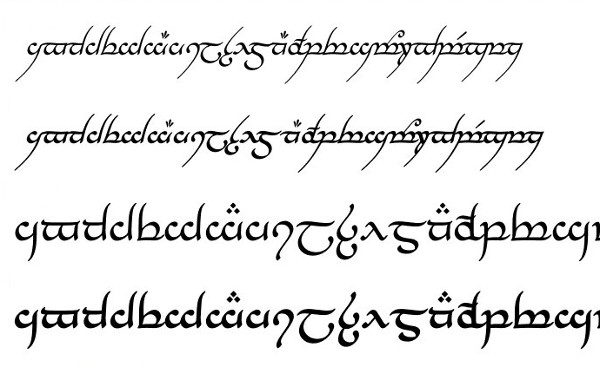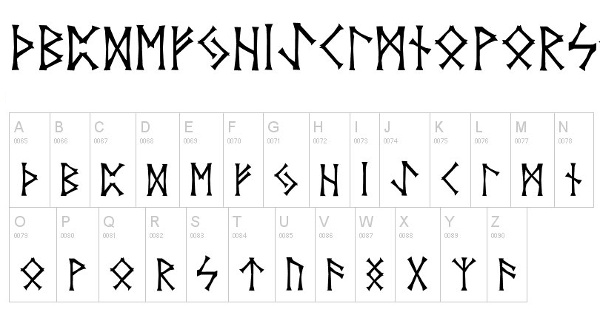
Die 28 besten kostenlosen Tattoo-Schriftarten 2020 für Ihre Körperkunst
Veröffentlicht: 2017-09-01Während Sie ein Tattoo mit (fast) jeder Schriftart entwerfen können, gibt es die Liste der besten kostenlosen Tattoo-Schriftarten, in der einige Schriftarten enthalten sind, damit Sie Ihren Tätowierungen eine wirklich aufmerksamkeitsstarke Note verleihen können. Tattoo-Fonts auf dieser Liste unterscheiden sich von denen mit exotischen Symbolen und gezielt illustrierten Glyphen bis hin zu eleganten Handschrift-Fonts. Mit wenigen Ausnahmen sind alle Schriftarten auf dieser Liste am besten für den persönlichen Gebrauch geeignet, das heißt, Sie können sie verwenden, um ein Tattoo für sich selbst zu entwerfen, aber für jede Art von industriellem Anlass müssen Sie sich an den Schriftartdesigner wenden und eine kaufen Lizenz.
1. Ananda Namaste – Kostenlose Tattoo-Schriftarten
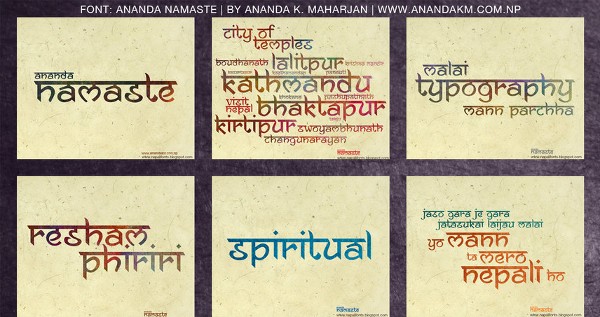
Diese atemberaubende Schriftart wurde durch Devanagari-Sanskrit-Skripte angeregt und von Ananda okay entworfen. Maharjan. Es handelt sich um lateinische Schriftzeichen, aber der charakteristische Überstrich verleiht ihm ein besonderes Aussehen. Im Gegensatz zu anderen Schriftarten auf dieser Platte ist Ananda Namaste für den industriellen Gebrauch kostenlos. Dass Sie es von der Webseite der Schneiderin deviantART in TTF-Struktur herunterladen können.
2. Blackletter – Kostenlose Tattoo-Schriftarten
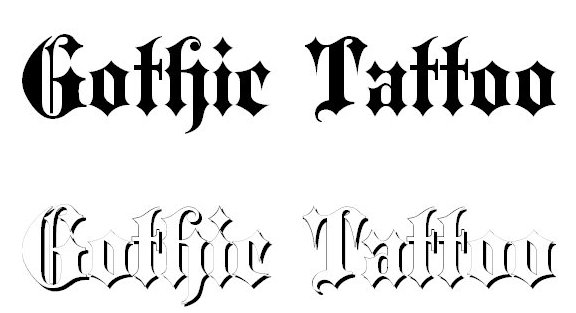
Top Free Tattoo Fonts „Blackletter“ ist eine fette, gotische Schriftart, die in zwei Versionen erhältlich ist, allgemein und beschreibend. Es ist auch für den industriellen Einsatz zu haben und wird auch im TTF-Layout heruntergeladen. Blackletter wurde von Dieter Steffmann entworfen und ist die beste Schriftart für jeden, der ein ziemlich normales, aber optisch ansprechendes Tattoo haben möchte.
3. Tribal – Kostenlose Tattoo-Schriftarten
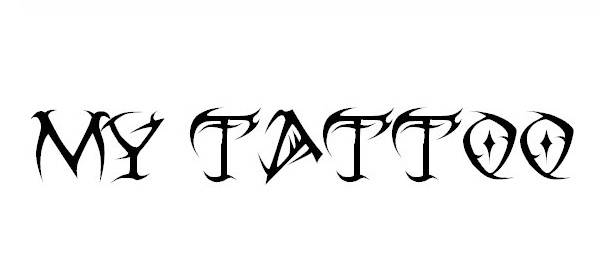
Die besten kostenlosen Tattoo-Schriftarten „Tribal“-Tattoos werden immer bevorzugt, also können Sie mit dieser Tattoo-Schriftart nichts falsch machen. Tribal ist eine scharf aussehende Schriftart, die auch für den geschäftlichen Gebrauch zu haben ist. Es kommt in zwei Stilen; jeweils TTF-Dateien. Ihr Tattoo wird wahrscheinlich lesbar und faszinierend genug sein, um Aufmerksamkeit zu erregen.
4. Bombora – Kostenlose Tattoo-Schriftarten
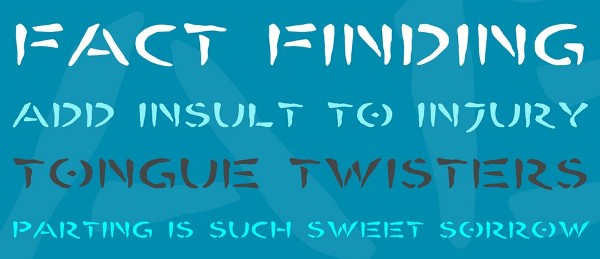
Bombora verwendet eine Art, die Tribal-Designs ähnelt, aber mit dickeren Strichen, die einem Pinsel ähneln. Es ist eine OTF-Schriftart, die in Tätowierungen, Überschriften oder auf Postern gleichermaßen zufriedenstellend aussieht.
5. Nurkholis – Kostenlose Tattoo-Schriftarten
Nurkholis ist eine der besten kostenlosen Tattoo-Schriftarten, das ist eine hochwertige Schriftart, die Kleinbuchstaben des lateinischen Alphabets verwendet und sie in einem kreativen Ansatz kombiniert, um Ihre Schrift wie eine arabische Schrift erscheinen zu lassen. Wenn Sie ein Fan der arabischen Kalligraphie sind, ist diese Schriftart ideal für Sie, egal ob Sie sie für Tätowierungen oder andere Zwecke verwenden möchten. Nurkholis ist eine TTF-Schriftart.
6. Straffällig
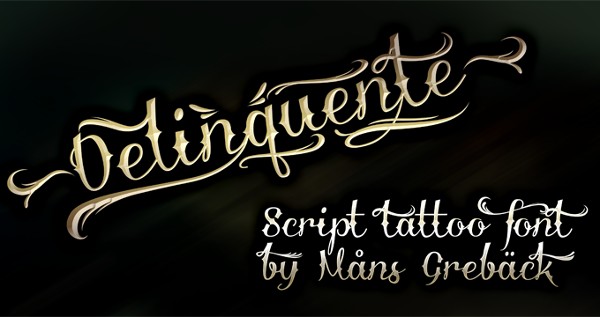
Delinquente ist eine seriös aussehende Schreibschrift mit satten Schwüngen. Es ist erstklassig, wenn Sie Ihr Tattoo offensichtlich und lesbar machen möchten. Es ist als TTF erhältlich
7. Tätowierung schwer
Top Free Tattoo Fonts „Tattoo Heavy“ verwendet dicke, unkonventionelle Striche, die besonders ansprechende Glyphen beeinflussen. Sie liegt im TTF-Layout vor und eignet sich für kurze Tattoos ebenso wie für Posterdesigns, Bandembleme und Titel. Bei kommerzieller Nutzung wenden Sie sich jedoch an den Ersteller.
8. Mardian
Mardian ist eine traditionelle, dezente Schreibschrift mit Zierinitialen, weshalb sie auch sehr gut als Monogrammschrift verwendet werden kann. Die Demovariante hilft einigen verbesserten Charakteren und ist in TTF-Struktur verfügbar. Für geschäftliche Nutzungsrechte müssen Sie die vollständige Schriftart erwerben.
9. Stammes-Tätowierung
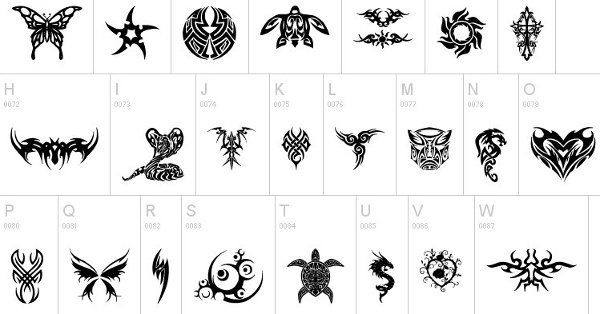
Sie denken vielleicht darüber nach, eine andere Schriftart mit Tribal im Titel, aber diese ist absolut anders als die vorherige Tribal Tattoo-Schriftart. Wie Sie feststellen werden, handelt es sich um eine Dingbat-Schriftart, was bedeutet, dass sie bestimmte Symbole und Formen anstelle von Zahlen und Buchstaben verwendet. Diese Symbole sind Standard-Tattoo-Motive, und diese Schriftart macht es für Sie praktisch, ein Tattoo-Design zusammenzustellen. Wählen Sie einfach ein Symbol aus, drucken Sie es aus und bringen Sie es zu Ihrem Tattoo-Shop.
10. Angilla
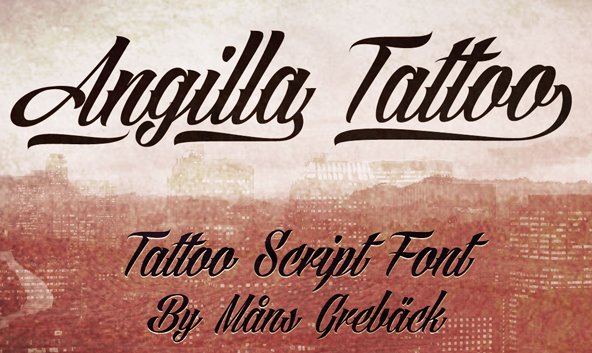
Angilla ist eine ziemlich ansprechende Schriftart mit dicken Schwüngen, die kalligrafischen Schriftarten huldigen. Ich kann sehen, dass es für Schlagzeilen und Posterdesigns so gut wie Tätowierungen verwendet wird. Welche Sie in TTF-Struktur herunterladen können.
11. Mittelalterliche Schreibschrift
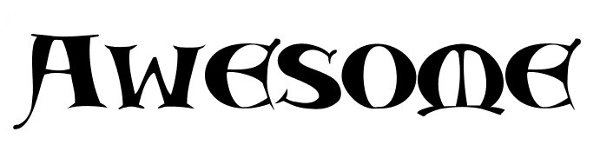
Medieval Scribish ist eine All-Caps-Tattoo-Schriftart mit einem erfinderischen und etwas mittelalterlichen Flair. Genau die richtigen Informationen, die für den industriellen Einsatz kostenlos sind! Laden Sie die TTF-Datei herunter und arbeiten Sie an Ihrem fantastischen Tattoo-Design.
27. Drache kommt
Diese stylische Schreibschrift mit langen, kalligraphischen Schwüngen lässt jedes Tattoo schick aussehen, ist aber besonders passend für Preise oder Namen Ihrer Liebsten in einem Tattoo-Design. Es ist eine OTF-Schriftart mit Unterstützung für multiplizierte Zeichen.
28. Buche – Kostenlose Tattoo-Schriftarten
Top Free Tattoo Fonts „Beech“ ist eine hochwertige Alternative für eine Tattoo-Schrift, wenn Sie ein geheimnisvolles, wundervolles Design erstellen möchten. Es ist eine dekorative TTF-Schrift mit sehr dicken Strichen.